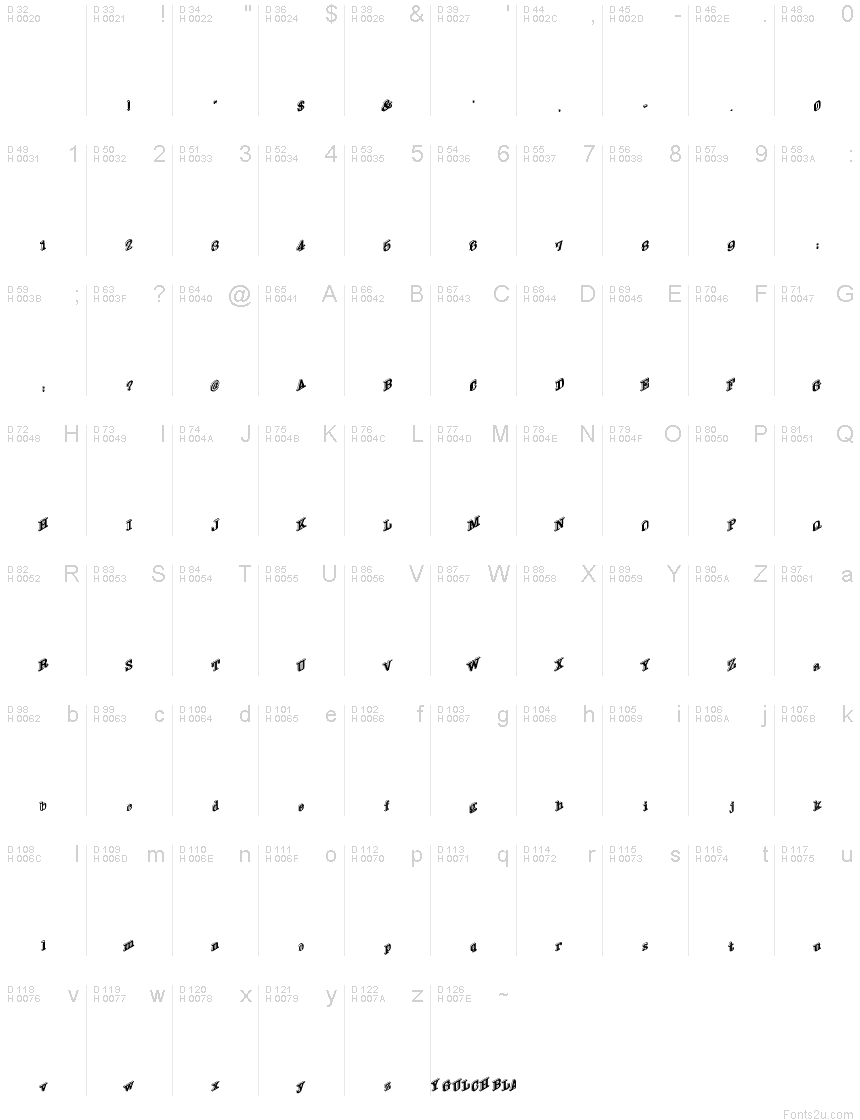
Dry Gulch Black, autorstwa J.F.Y. Daniela Gauthiera z GautFonts, to darmowy westernowy krój 3D typu display, który emanuje stylem dawnych szyldów saloonowych. Litery opierają się na masywnych formach typu slab oraz efekcie rzeźbionego cienia, a wywinięte końcówki i ścięte rogi nadają mu ten zakurzony, teatralny klimat Dzikiego Zachodu.
Świetnie sprawdza się na plakatach, w brandingu whiskey lub barbecue, na ulotkach festiwalowych, planszach tytułowych, grafikach do gier i krótkich nagłówkach, gdzie ten wypukły, malowany ręcznie wygląd robi świetną robotę. Jako darmowy font, sprawdza się również przy monogramach, inicjałach i szkicach logo, zwłaszcza gdy szukasz wyrazistego westernowego charakteru bez konieczności tworzenia rozbudowanych tekstów.
DryGulchBlack by J.F.Y.Daniel Gauthier - GautFonts